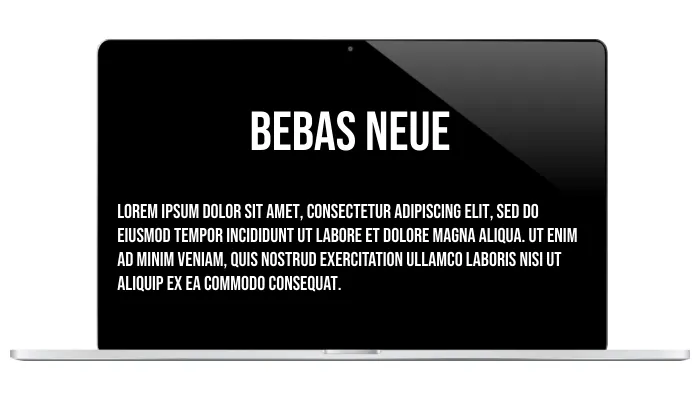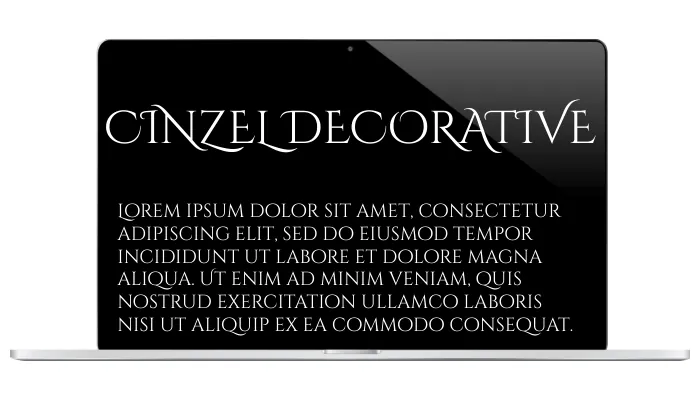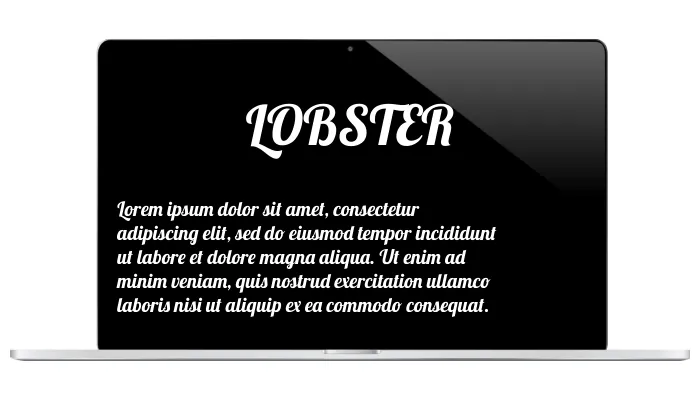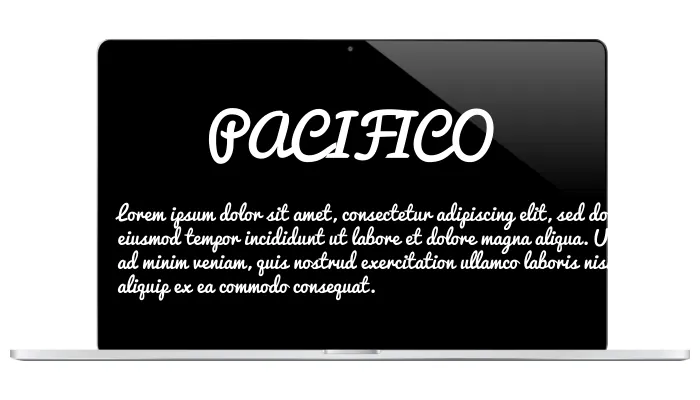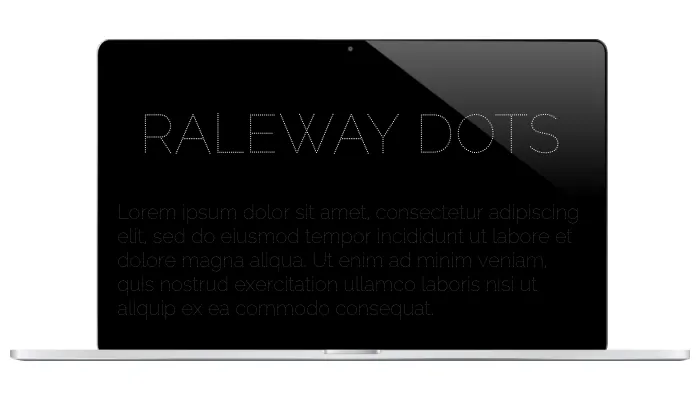
Las tipografías decorativas son las que dan personalidad a un diseño: un título, un logo, un cartel o una portada. No sirven para leer un párrafo entero, pero sí para que algo destaque y transmita el tono adecuado. Te he seleccionado 10 gratis, con su enlace y licencia, y te cuento cómo elegir la que encaja en tu proyecto.
Cómo elegir una tipografía decorativa
Antes de descargar, piensa en tres cosas: el tono (elegante, divertido, retro), dónde va a leerse (pantalla o impreso) y que tenga los caracteres que necesitas (tildes y ñ, sobre todo). Una decorativa preciosa sin ñ te va a dar problemas en español.
10 tipografías decorativas gratis
Bebas Neue
Audaz, sin remates y muy versátil. Se ha vuelto una favorita para títulos por su fuerza y elegancia. Perfecta cuando quieres impacto en mayúsculas.
Lobster
Una script con curvas suaves y aire retro cálido. Ideal para invitaciones, tarjetas o logos que buscan diversión y creatividad.
Pacifico
Manuscrita, suave y con aire playero. Transmite relax y frescura, perfecta para moda, viajes o estilo de vida.
Cinzel Decorative
Clásica y elegante, inspirada en las formas del Renacimiento. Aporta distinción a invitaciones formales, tarjetas y marcas de lujo.
Abril Fatface
Serif de contraste alto, con un toque editorial y elegante. Funciona genial en titulares de revista y portadas.
Playfair Display
Serif sofisticada de estilo clásico. Combina de maravilla con una sans sencilla para un look elegante y atemporal.
Alfa Slab One
Una slab serif gruesa y contundente. Perfecta para carteles y titulares que tienen que verse de lejos.
Monoton
Tipografía de líneas dobles con aire retro de neón. Muy llamativa para logos y titulares con un guiño ochentero.
Righteous
Geométrica y redondeada con carácter art déco suave. Buena para marcas modernas y amables.
Raleway Dots
Original y punteada: cada letra se compone de puntos. Vanguardista para títulos que buscan destacar entre la multitud.
Decorativas frente a ornamentales
«Decorativa» es el paraguas amplio de fuentes con personalidad. Las ornamentales son un subtipo concreto, con florituras y adornos clásicos. Si buscas ese estilo recargado, míralas aquí: tipografías ornamentales.
Preguntas frecuentes
¿Qué es una tipografía decorativa?
Una fuente pensada para destacar (títulos, logos, carteles), con personalidad. No está hecha para textos largos.
¿Cuándo no debería usar una decorativa?
En párrafos largos: cansan la vista. Resérvalas para titulares y elementos que quieras resaltar.